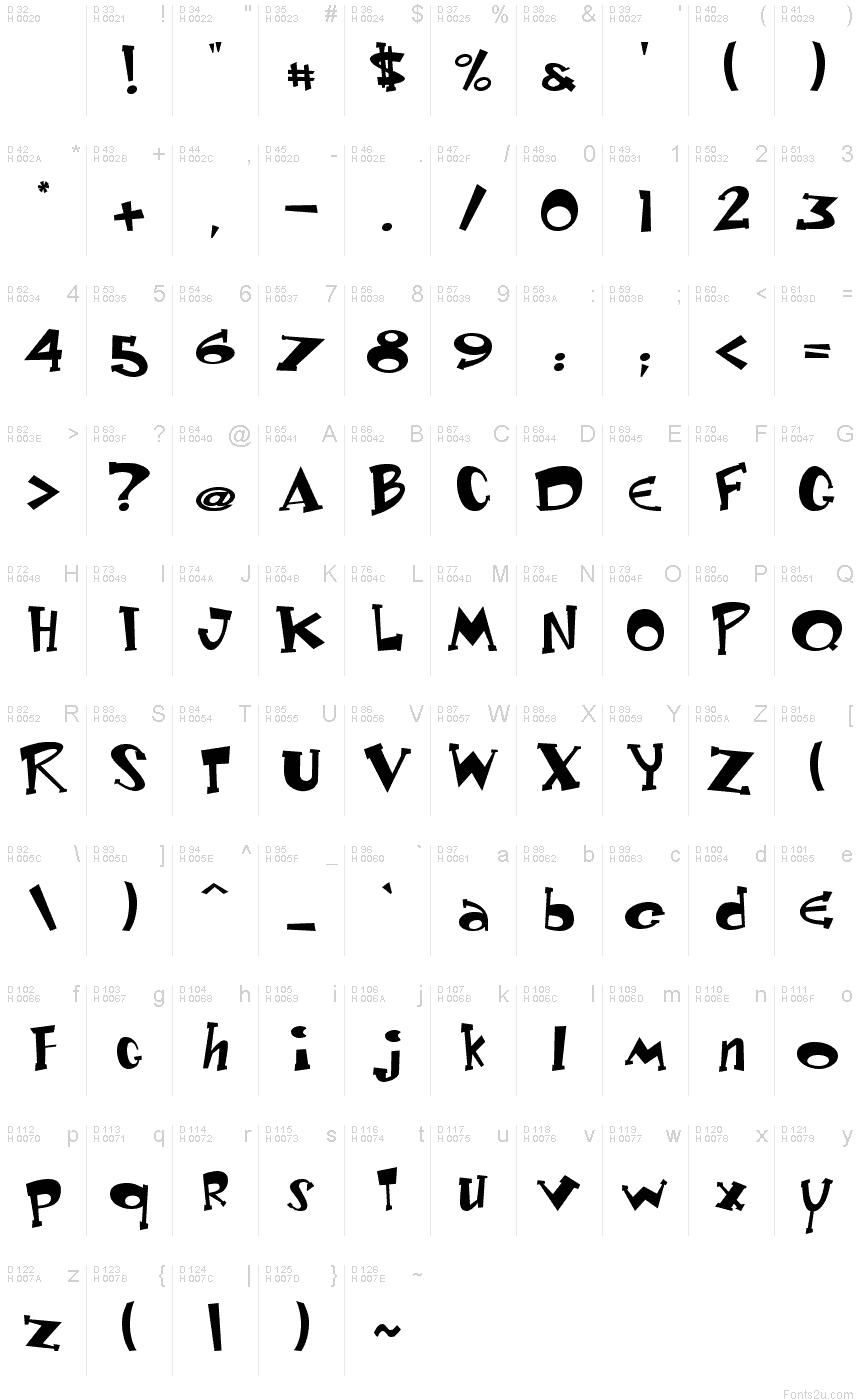
Keyster autorstwa Chrisa Browna to darmowy komiksowy font typu display, pełen dzikiej energii w stylu wycinanki. Wysokie, nieco krzywe litery wyglądają, jakby zostały wycięte z czarnego papieru i przypięte pod dziwnymi kątami, co nadaje każdemu słowu skoczny, lekko psotny charakter. Masywne kształty, ostre krawędzie i zabawne pochylenie sprawiają, że nagłówki wyskakują ze strony niczym krzyk namalowany grubym markerem.
Ten darmowy font świetnie sprawdza się na dziecięcych plakatach, zaproszeniach na imprezy, okładkach komiksów, zinach, miniaturach na YouTube oraz w oryginalnych logotypach gier i aplikacji. Użycie Keyster w dużym rozmiarze pozwala w pełni wybrzmieć jego krzywemu rytmowi i wyrazistym sylwetkom. W tekście głównym warto połączyć go z czystym krojem bezszeryfowym, aby zachować czytelność przy jednoczesnym zachowaniu chaotycznej zabawy.
Keyster